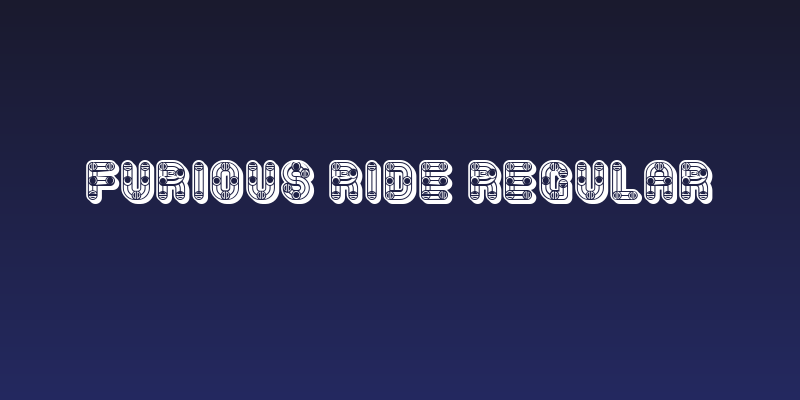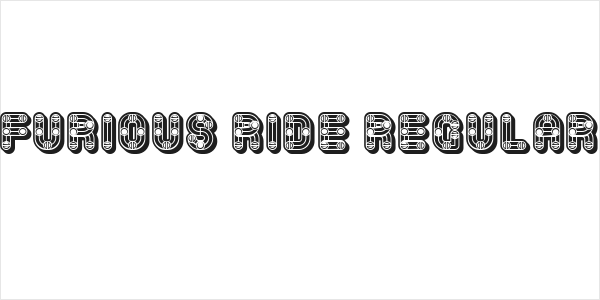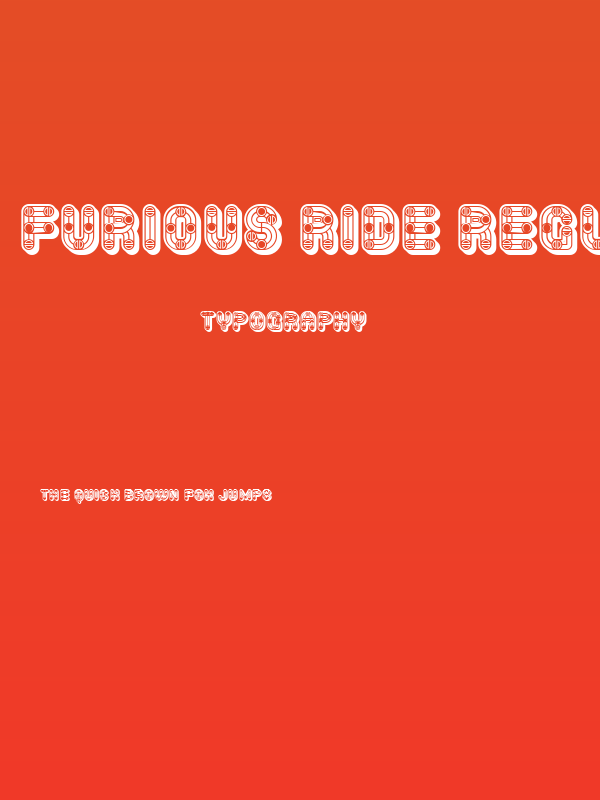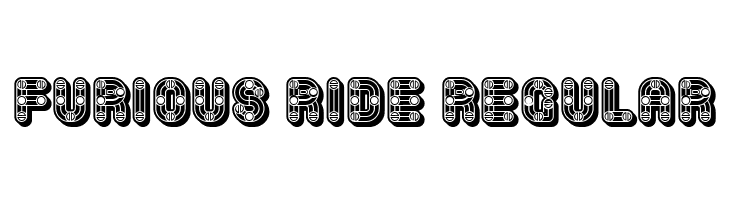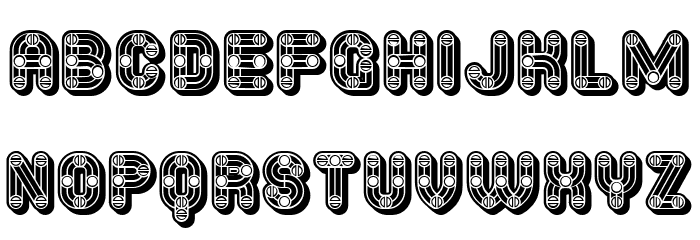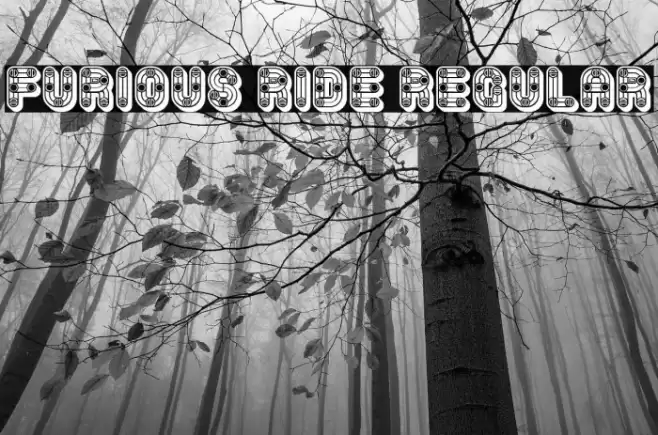
Furious Ride Regular Font
| Estilo geral | Modern, Futuristic |
| Projetos propostos | Ideal for technology-themed posters, video game titles, branding for tech companies, and futuristic designs. |